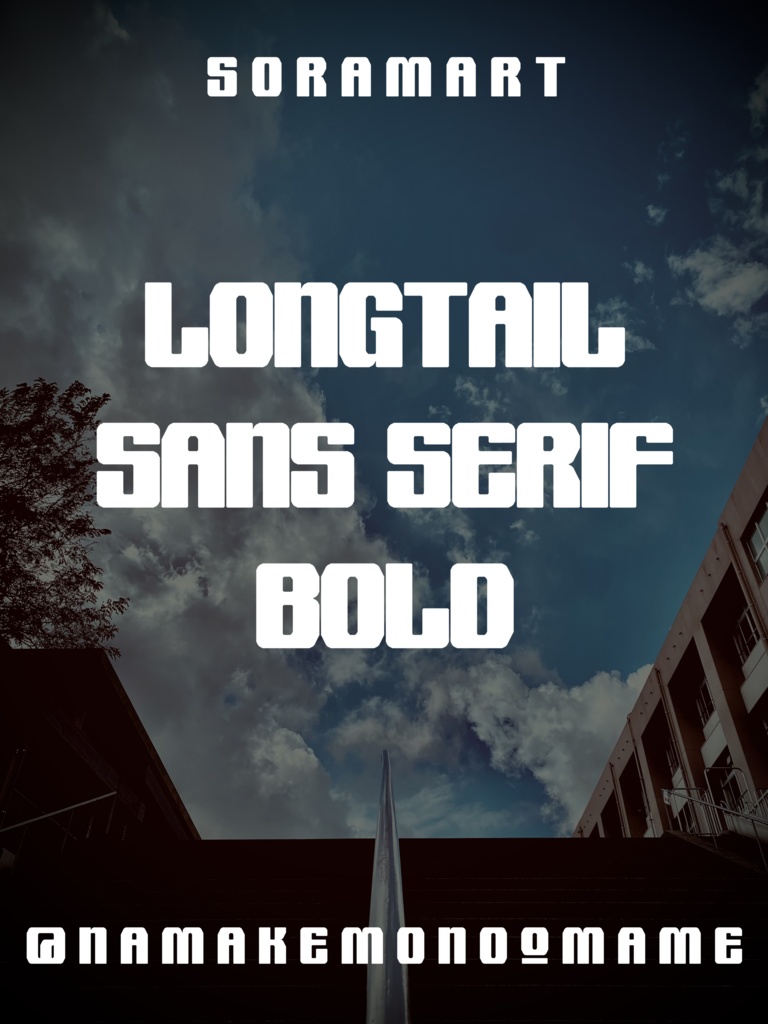
そらマートフォントデータ”Longtail Sans Serif Bold”ダウンロード商品¥ 2,500カートに入れるギフトとして贈る「ギフトとして贈る」とはシンプルなスタイルのあしなが縦長フォントを太字化した "Longtail Sans Serif Bold" です。 「TrueTypeフォントファイル」という形式です。 ダウンロードした後、Zipファイル内のデータをインストールしてお使いください。 このフォントは商用利用可となっております。 お客様の制作・創作活動のお役に立てれば幸いです。 ※使用上の注意事項などは、添付のReadmeをお読みください。そらマートFANBOX開設中フォント・書体フォントデータ”Tonik Crate”そらマート¥ 0フォント・書体フォントデータ”Vapor Sprout Edge”そらマート¥ 2,500フォント・書体フォントデータ”Vapor Sprout Wide”そらマート¥ 2,500フォント・書体フォントデータ”Vapor Sprout”そらマート¥ 2,500フォント・書体フォントデータ”Star Shoot Ray”そらマート¥ 2,500フォント・書体フォントデータ”Star Shoot Black Wide”そらマート¥ 2,500フォント・書体フォントデータ”Star Shoot Black”そらマート¥ 2,500フォント・書体フォントデータ”Mars Invader Balloon”そらマート¥ 2,500フォント・書体フォントデータ”Mars Invader Wide”そらマート¥ 2,500フォント・書体フォントデータ”Mars Invader”そらマート¥ 2,500フォント・書体フォントデータ”Rock Cut Serif”そらマート¥ 2,500フォント・書体フォントデータ”Rock Cut Drop Wide”そらマート¥ 2,500フォント・書体フォントデータ”Rock Cut Drop”そらマート¥ 2,500フォント・書体フォントデータ”Longtail Sans Serif Slashed”そらマート¥ 2,500フォント・書体フォントデータ”Longtail Sans Serif”そらマート¥ 2,500フォント・書体フォントデータ”Pretty Commando”そらマート¥ 2,500フォント・書体フォントデータ”Abyss Dive Punk Retro”そらマート¥ 2,500フォント・書体フォントデータ”Abyss Dive Punk Wide”そらマート¥ 2,500フォント・書体フォントデータ”Abyss Dive Punk”そらマート¥ 2,500フォント・書体フォントデータ”Emerald Sphere Sprite”そらマート¥ 2,500もっと見る